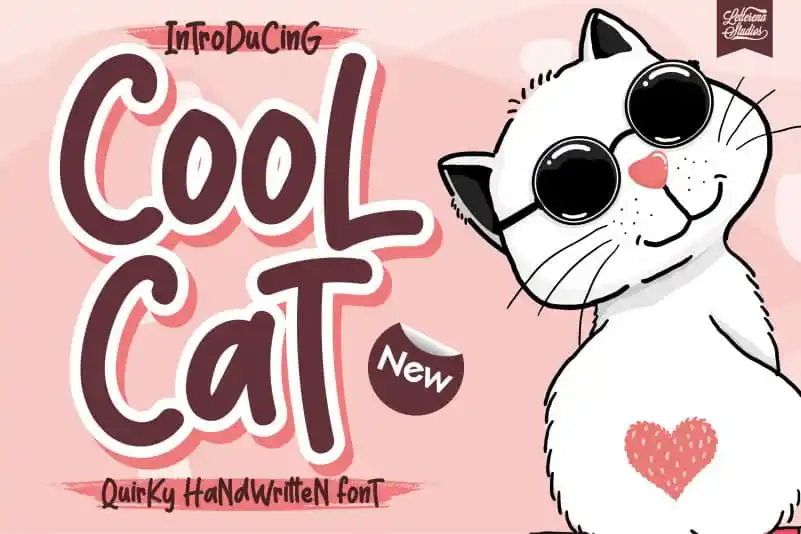
Cool Cat Display Font – Fonte Grátis
Cool Cat Display Font
A Cool Cat Display Font é uma linda escolha para quem quer dar um toque único a seus projetos DIY. Esta fonte de exibição tem um estilo único e um visual encantador, que vai fazer você cair de amores por sua aparência descontraída e animada. Seja para marcar seu próprio livro com capa reciclada ou criando uma caixa de doces personalizada, a Cool Cat Display Font é perfeita para aqueles projetos em que o detalhe faz toda a diferença. Ela traz vida à sua criação, tornando-a única e divertida, sem perder seu charme autêntico. Não hesite em experimentar a fonte letterenastudios para adicionar um toque especial aos seus trabalhos manuais.